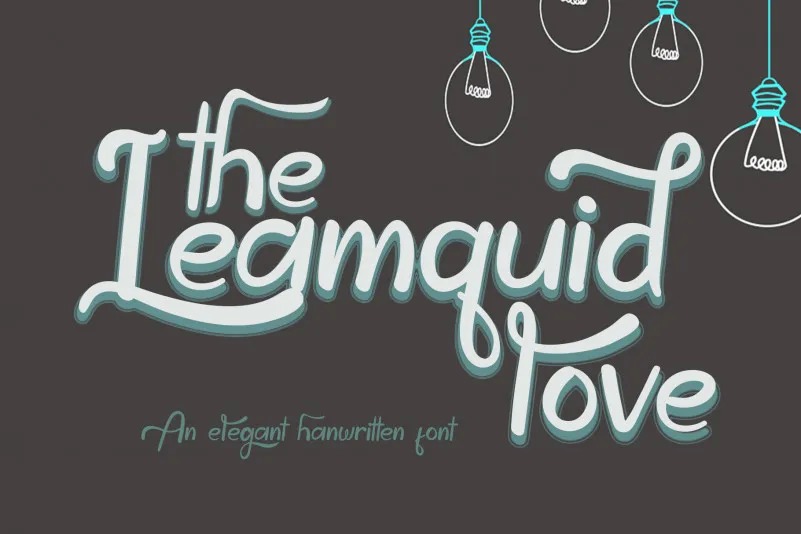
The Leamquid Love Script Font – Fonte Grátis
The Leamquid Love Script Font
A fonte “The Leamquid Love Script Font” é uma escolha excepcional para aqueles que valorizam a mistura perfeita entre clássica elegância e modernidade fresca. Essa fonte mantém os elementos distintivos do estilo de escrita, mas adicionando um toque contemporâneo e revigorante. Seu formato versátil é ideal para uma infinidade de ideias criativas, desde o design dos recados até a criação de logotipos e estaçãorios. É perfeita para designers que valorizam harmonia e sofisticação em suas produções digitais ou impressas. Com “The Leamquid Love Script Font”, você pode criar um estilo único que se destaca, seja em uma carta personalizada ou em uma embalagem de produto.